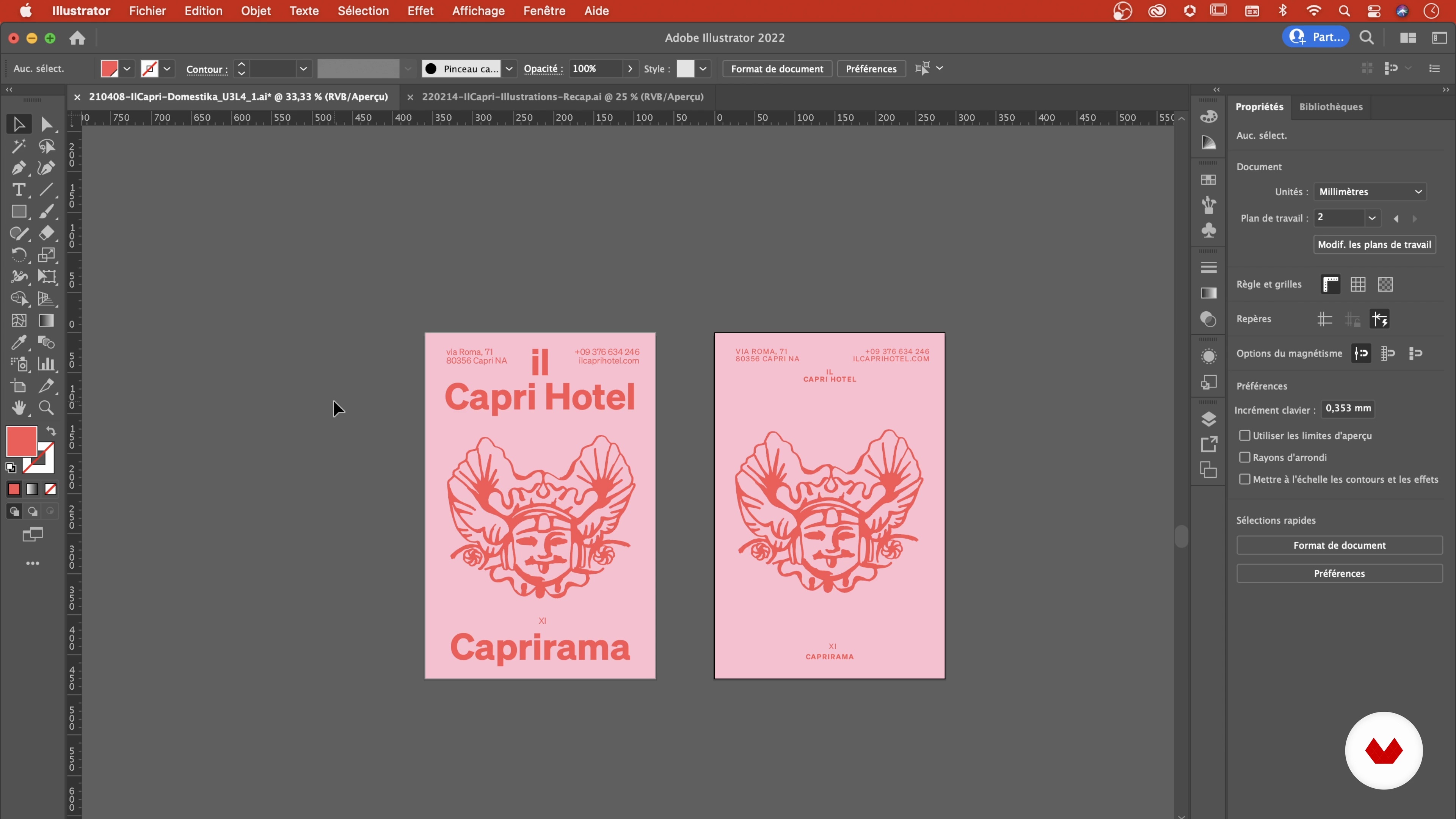
La typographie et la composition de visuels
À propos de la leçon : La typographie et la composition de visuels
“Maintenant, vous verrez quelles sont les questions à se poser quant aux choix typographiques qui, eux aussi, sont une part intégrante de l’identité globale. ”
Dans cette leçon, Fakepaper aborde le sujet : La typographie et la composition de visuels, qui fait partie du cours Domestika en ligne : Création d’une identité visuelle complète pour un lieu. Apprenez à créer une identité visuelle globale pour un lieu, du logo à la typographie en passant par un plan de site complet.
“La typographie et la composition de visuels Maintenant que Nolwenn a fini la vectorisation du corpus d'illustrations, on va passer à toute la phase de recherche autour de la typographie et voir comment l'intégrer à l'identité. Lors d'une discussion informelle avec Nolwenn, on s'est dit que ce serait intéressant d'utiliser l'iconographie des cartes de tarot italien, tout simplement parce qu'en fait, on était à la recherche de références qui soient en lien avec l'Italie et on voulait faire référence à toute cette imagerie-là et voir comment on pouvait la réinterpréter et la réexploiter. Je vo...”